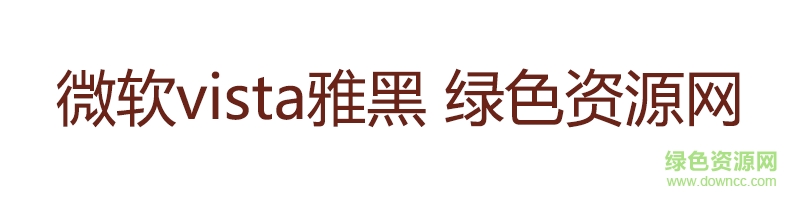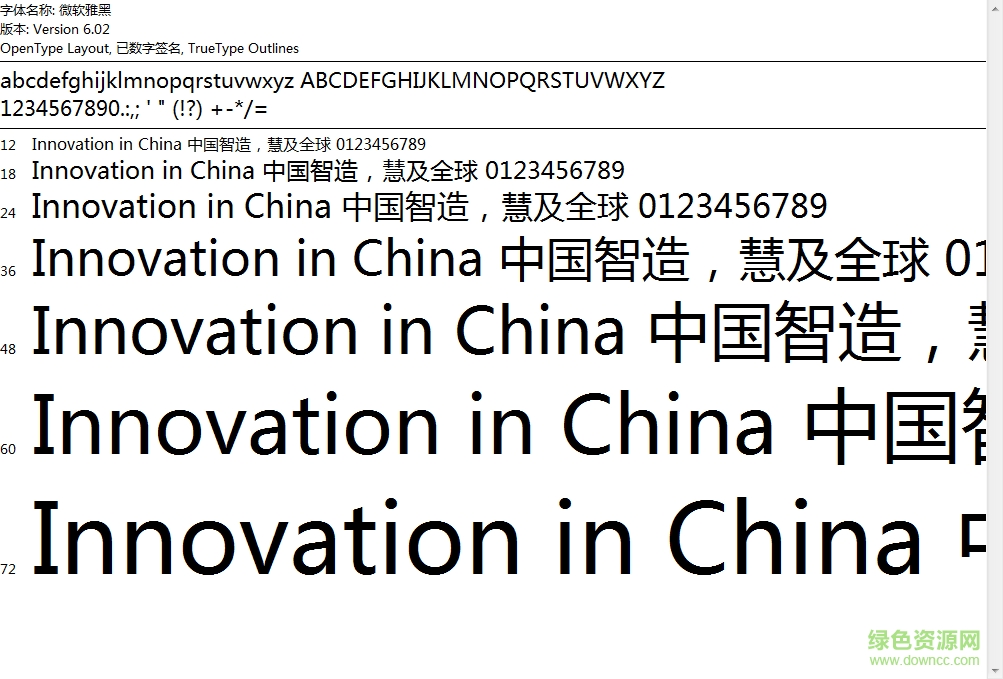
微軟vista雅黑字體是一款vista雅黑設(shè)計(jì)方面的字體,字型端莊優(yōu)雅、簡潔大氣,適用于平面設(shè)計(jì)、廣告設(shè)計(jì)、排版印刷等領(lǐng)域,綠色資源網(wǎng)提供最全最新的中英文字體素材,歡迎下載使用!
微軟vista雅黑筆觸較為粗實(shí),字形呈現(xiàn)細(xì)長狀態(tài),具有很好的視覺影響力,適合應(yīng)用于藝術(shù)設(shè)計(jì)、平面宣傳設(shè)計(jì)、網(wǎng)頁設(shè)計(jì),海報(bào)設(shè)計(jì)等應(yīng)用。